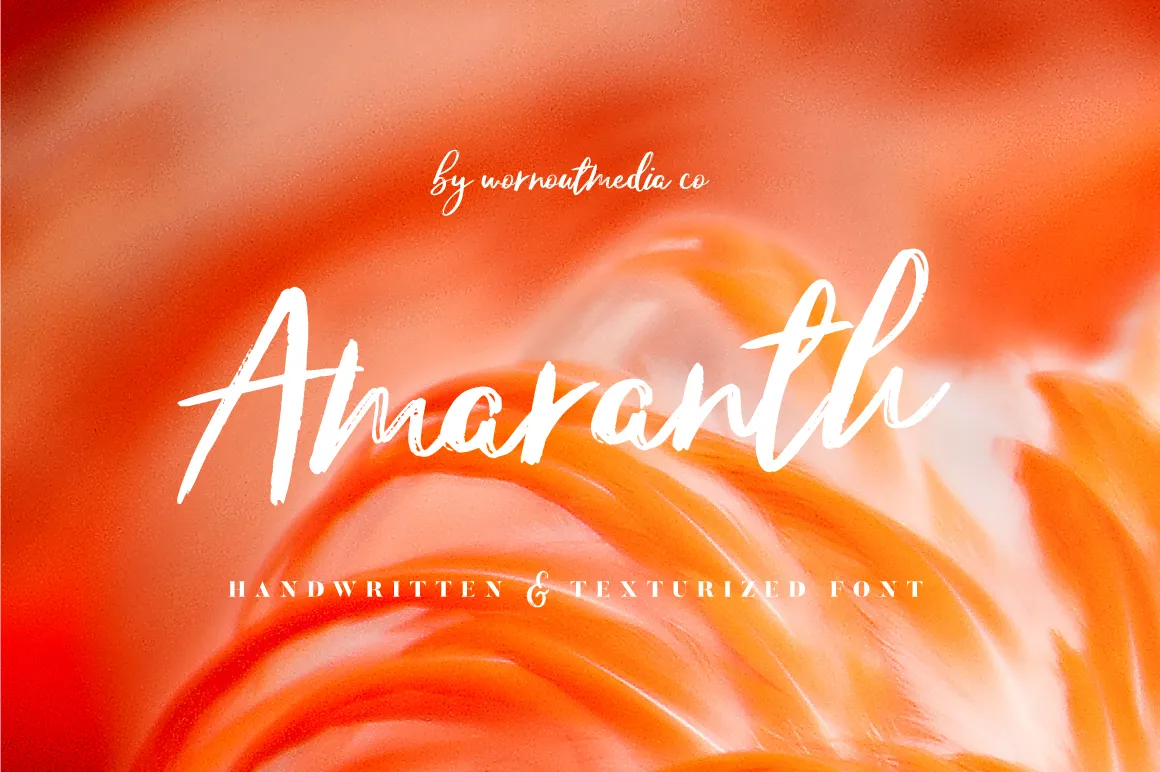
Amaranth Handwritten Font – Download Grátis
Amaranth Handwritten Font é uma elegante escolha para qualquer projeto que busque um toque suave e personalizado. Desenvolvida pela Worn Out Media Co., esta font é uma opção premium disponível na Creativemarket, mas hoje está gratuitamente à sua disposição para download. Com seu traçado delicado e estilo artesanal, Amaranth Handwritten é perfeito para criar textos agradáveis e personalizados que transmitem charme e sofisticação. Essa font brush é ideal para designers gráficos que buscam um elemento único no design de seus projetos, seja em cartazes, cartões de visita ou designs digitais. Em uma era onde o detalhe importa, Amaranth Handwritten traz a sua marca mais perto do coração do seu público com um touch elegante e único.